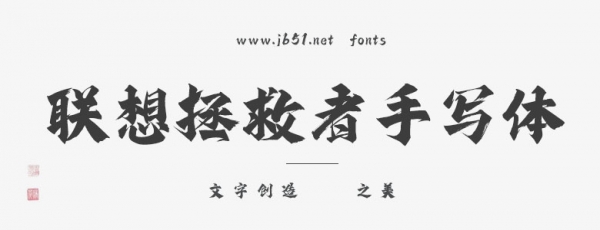
聯(lián)想拯救者手寫體,為更好地呈現(xiàn)聯(lián)想拯救者游戲本特色,書寫時(shí)融入了堅(jiān)毅果敢和強(qiáng)勢進(jìn)取的文化基因,筆墨酣暢灑脫、書寫鏗鏘有力。勾畫遒勁有力、勁健生動,針對“游戲影音本”產(chǎn)品定位作出獨(dú)特設(shè)計(jì),凸顯拯救者“極速”的產(chǎn)品特色。歡迎喜歡此字體的朋友前來下載使用。